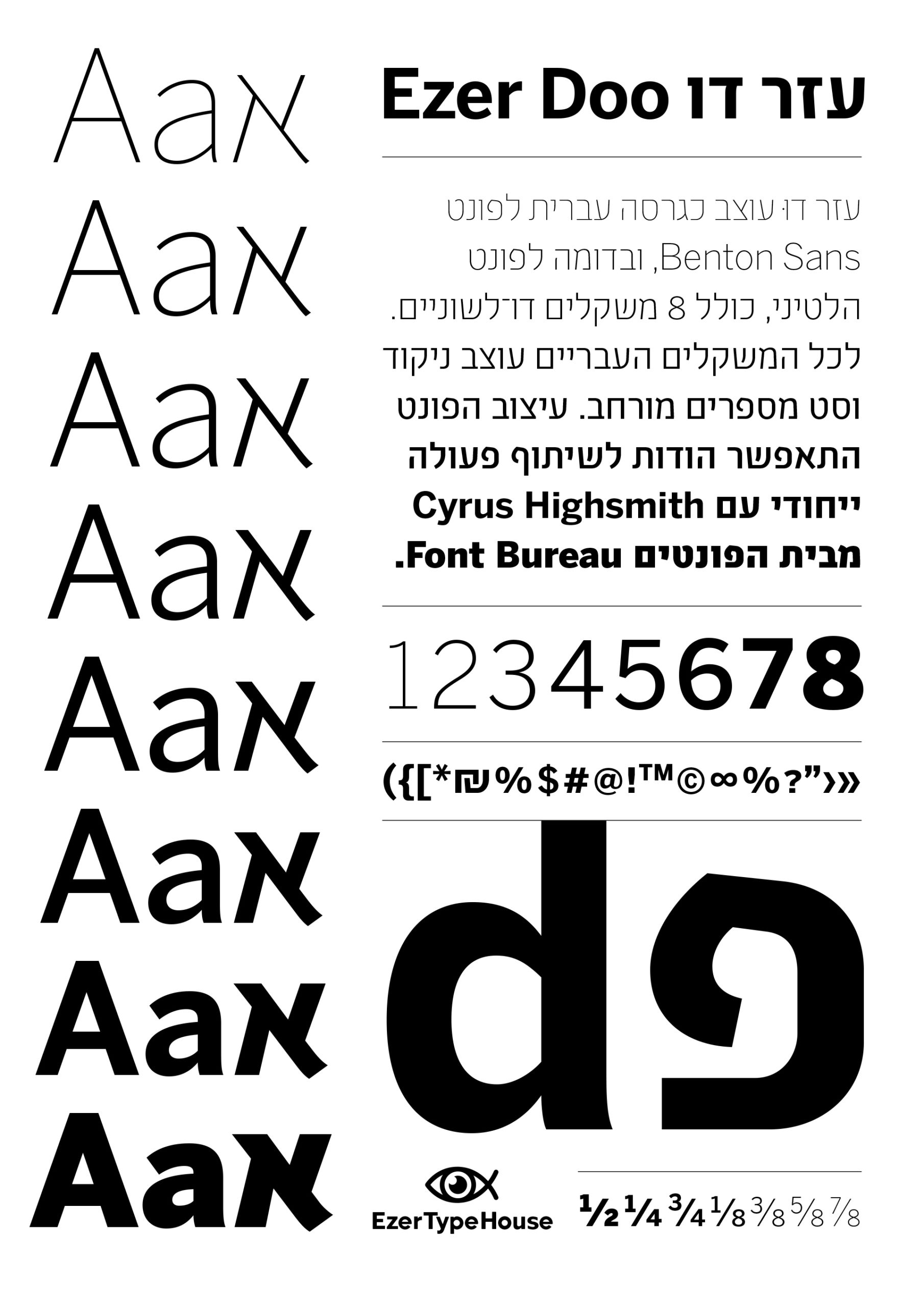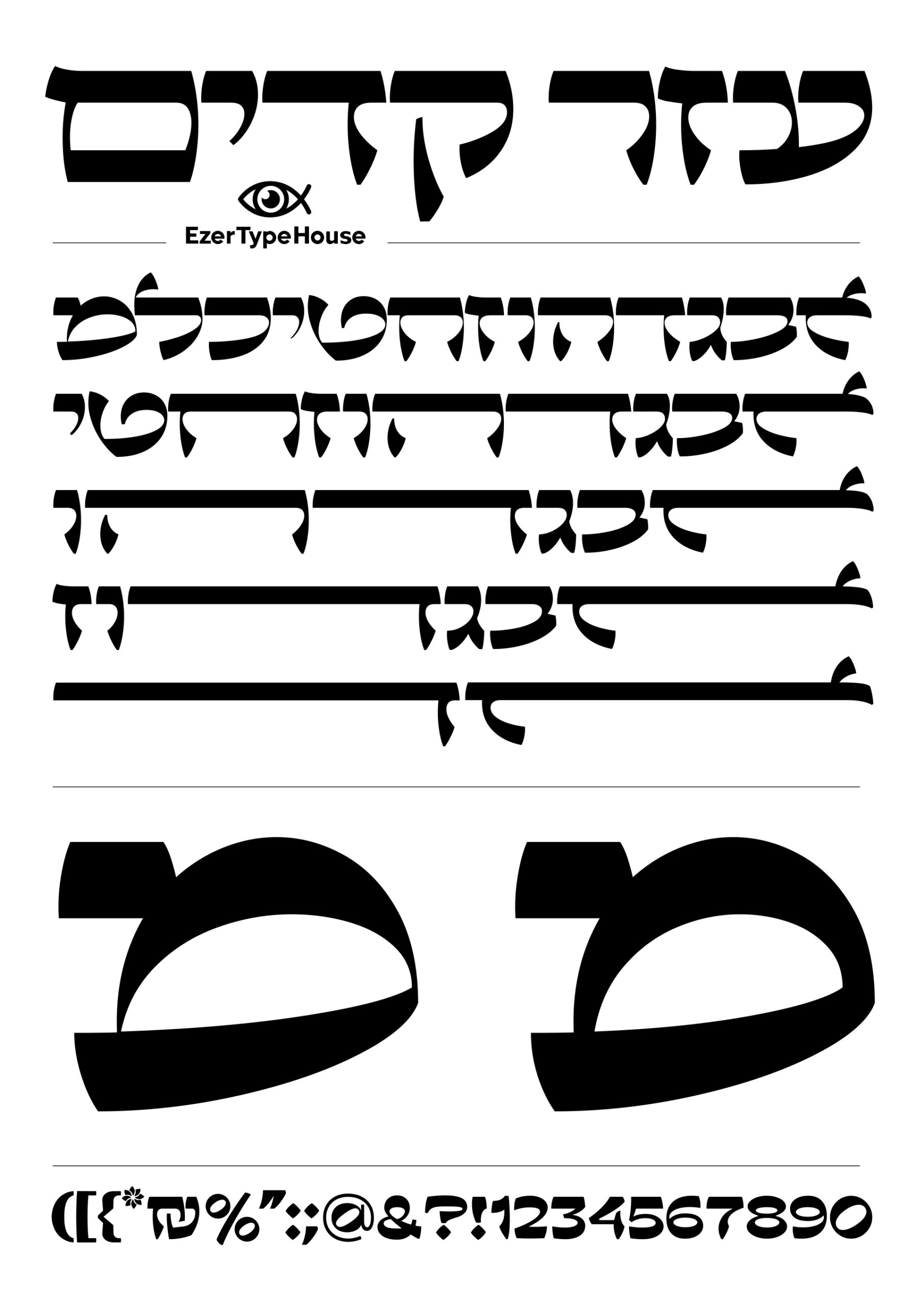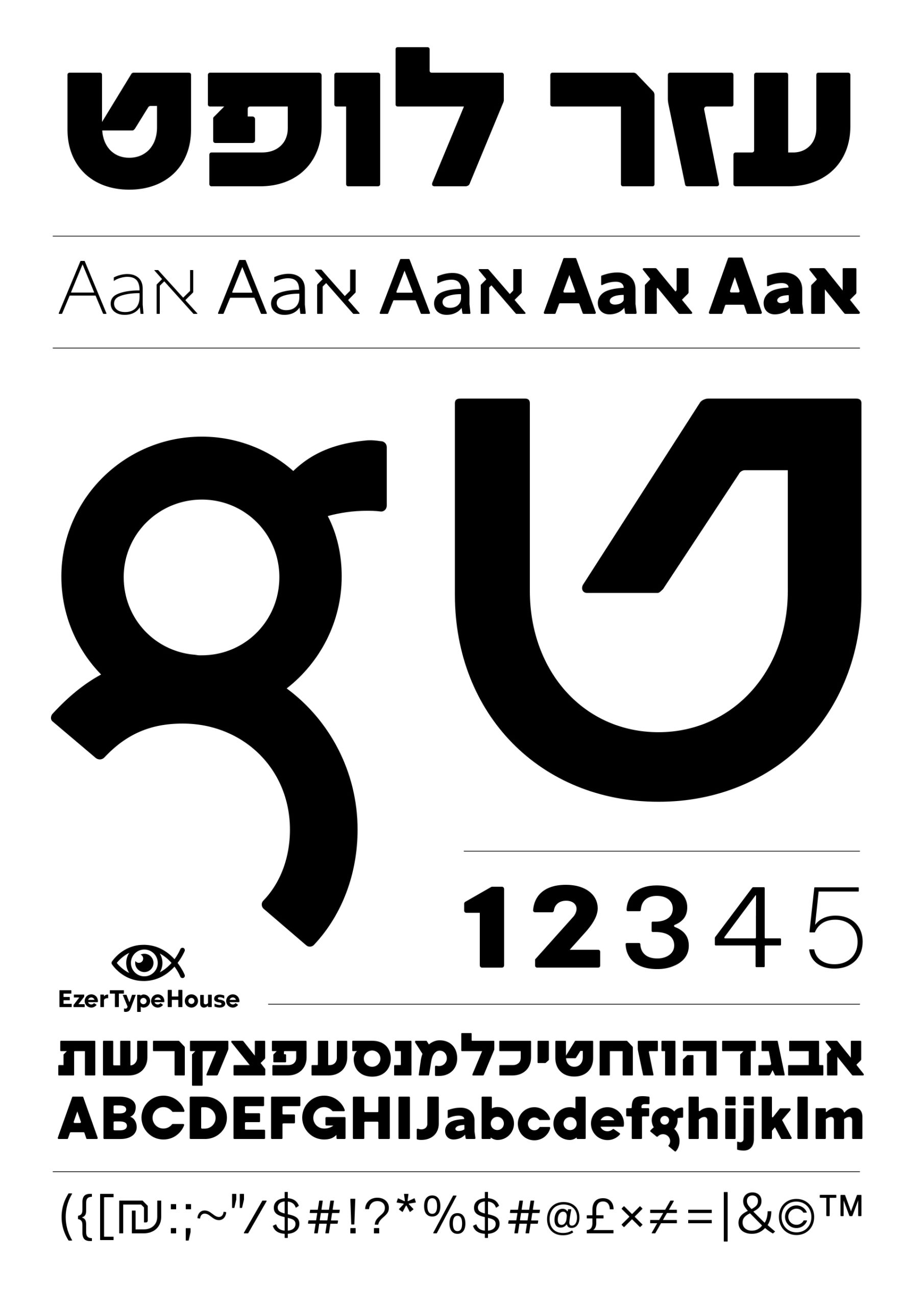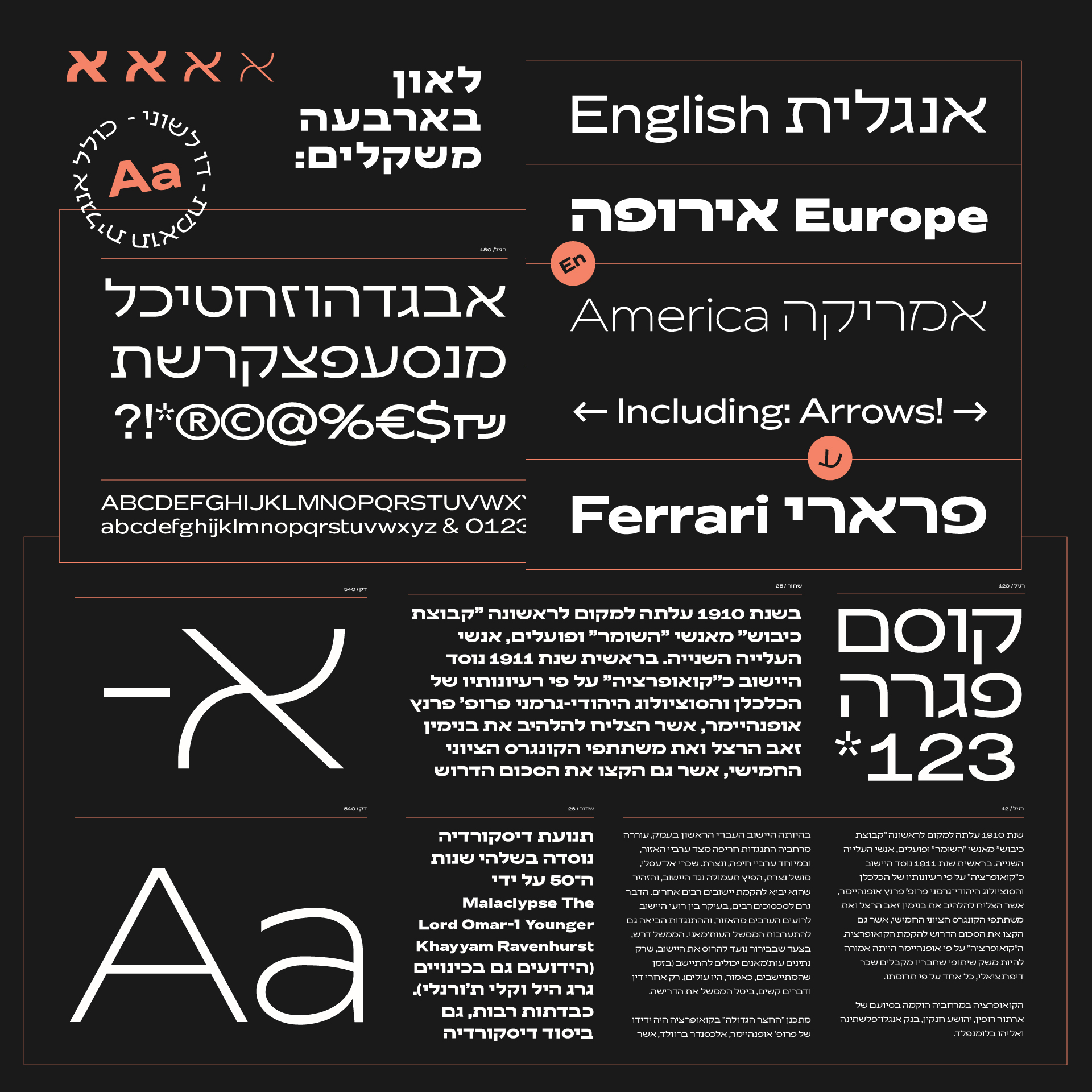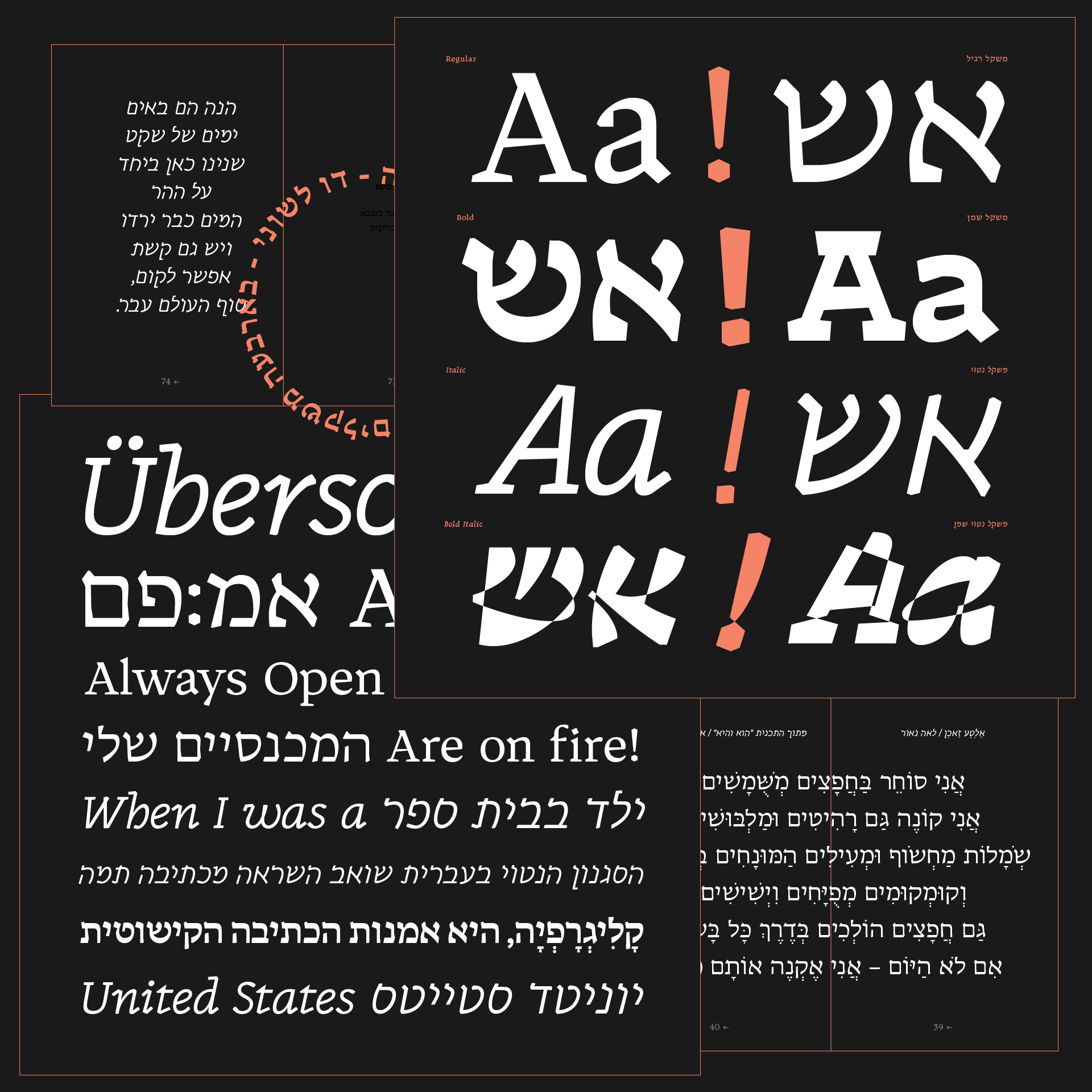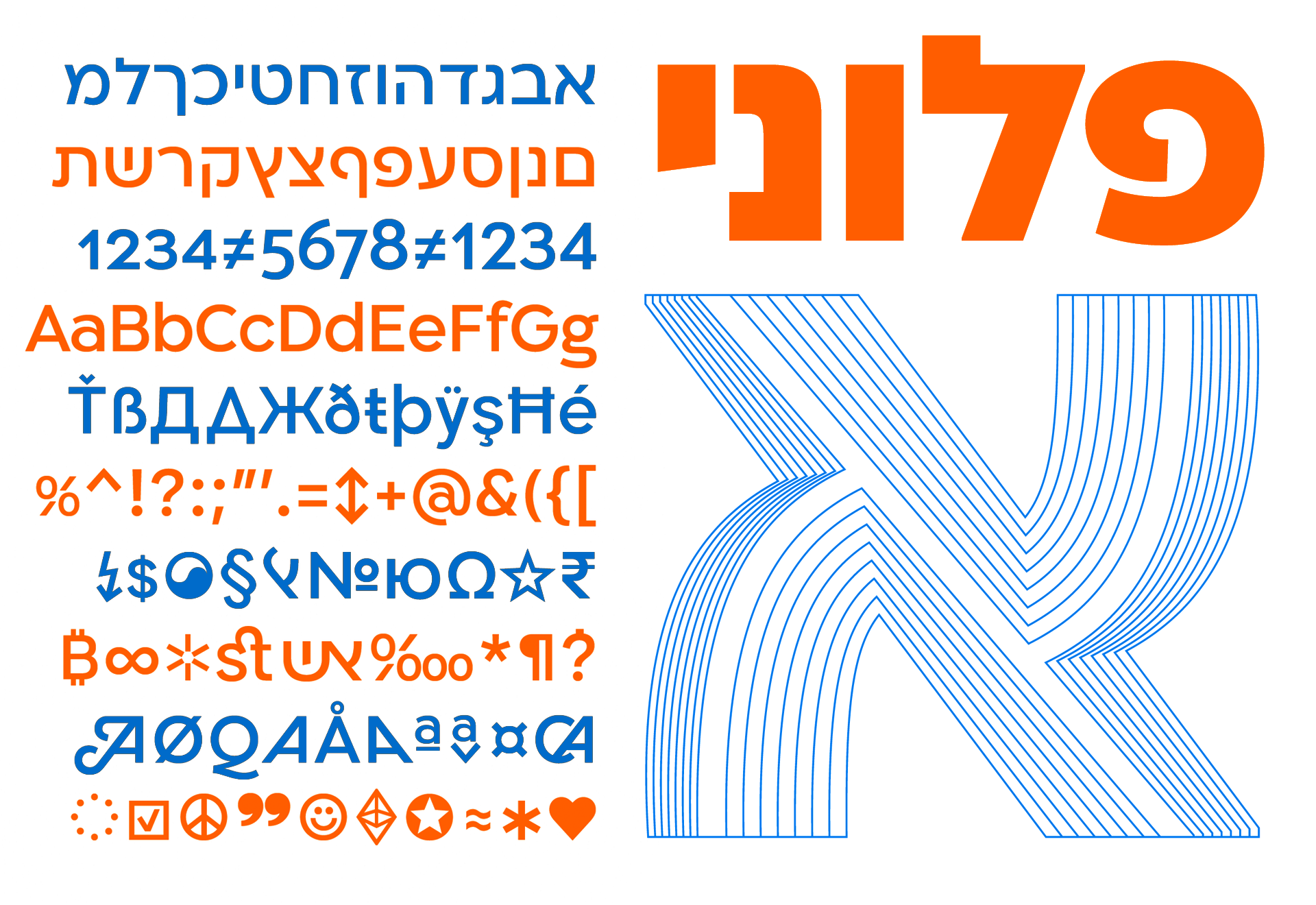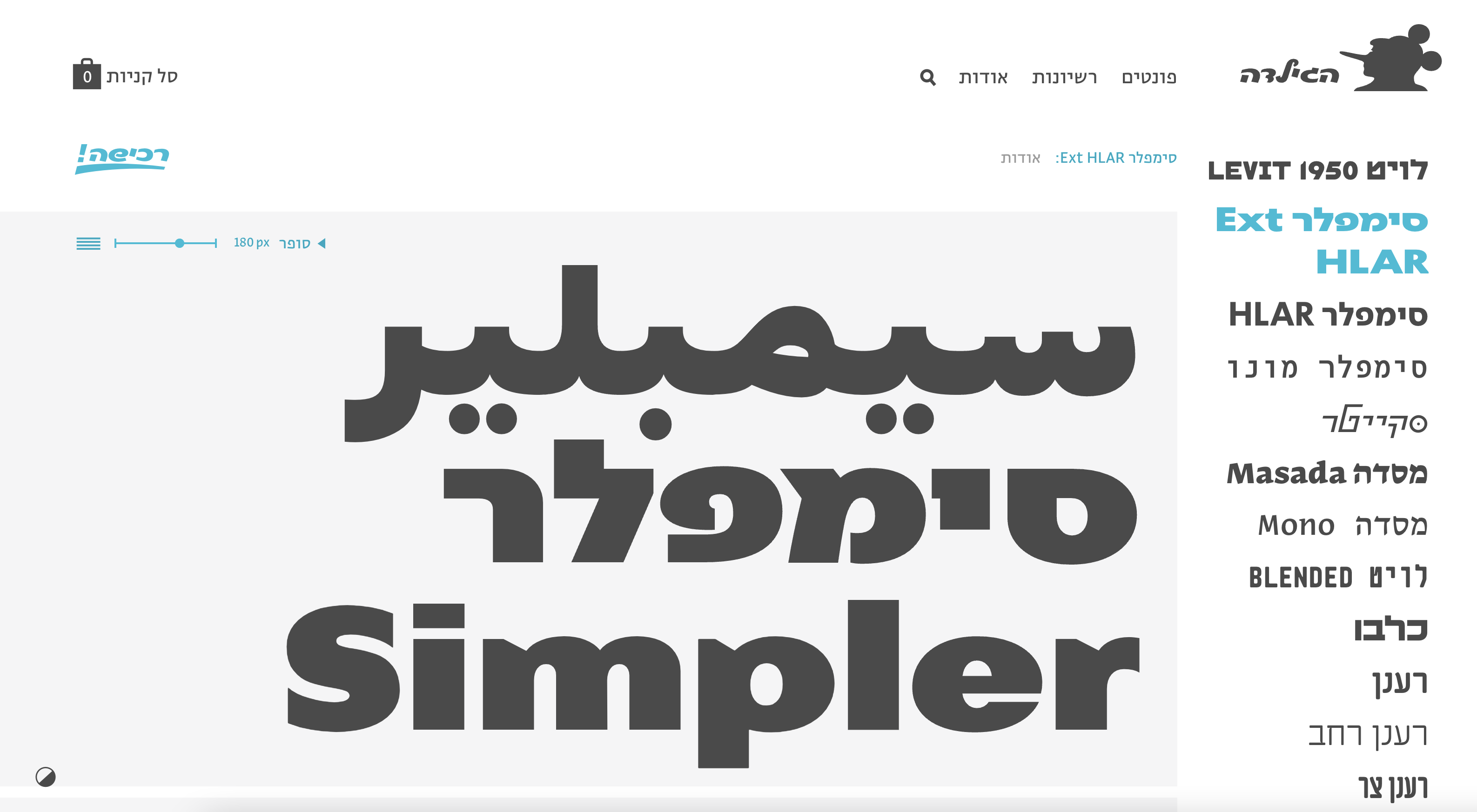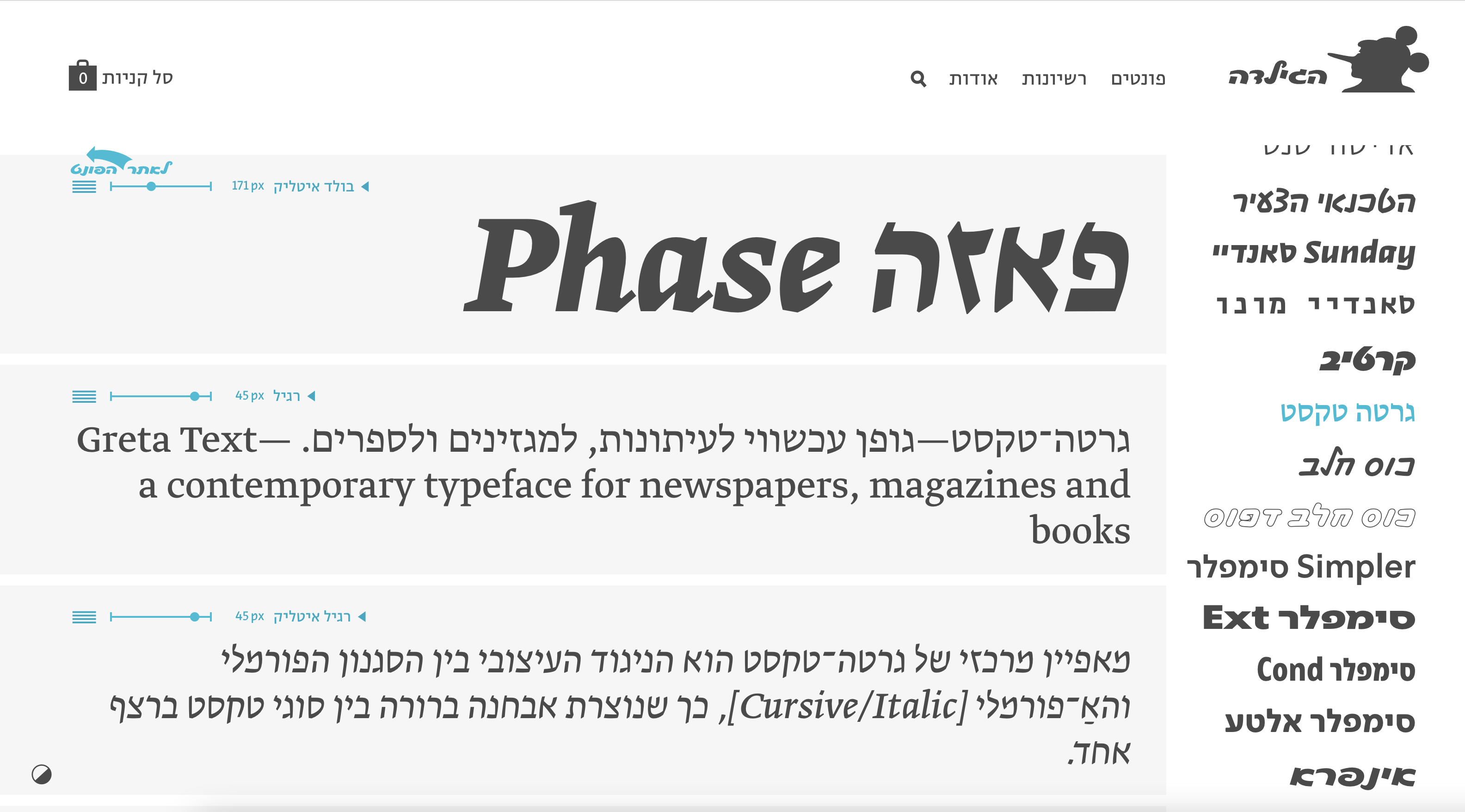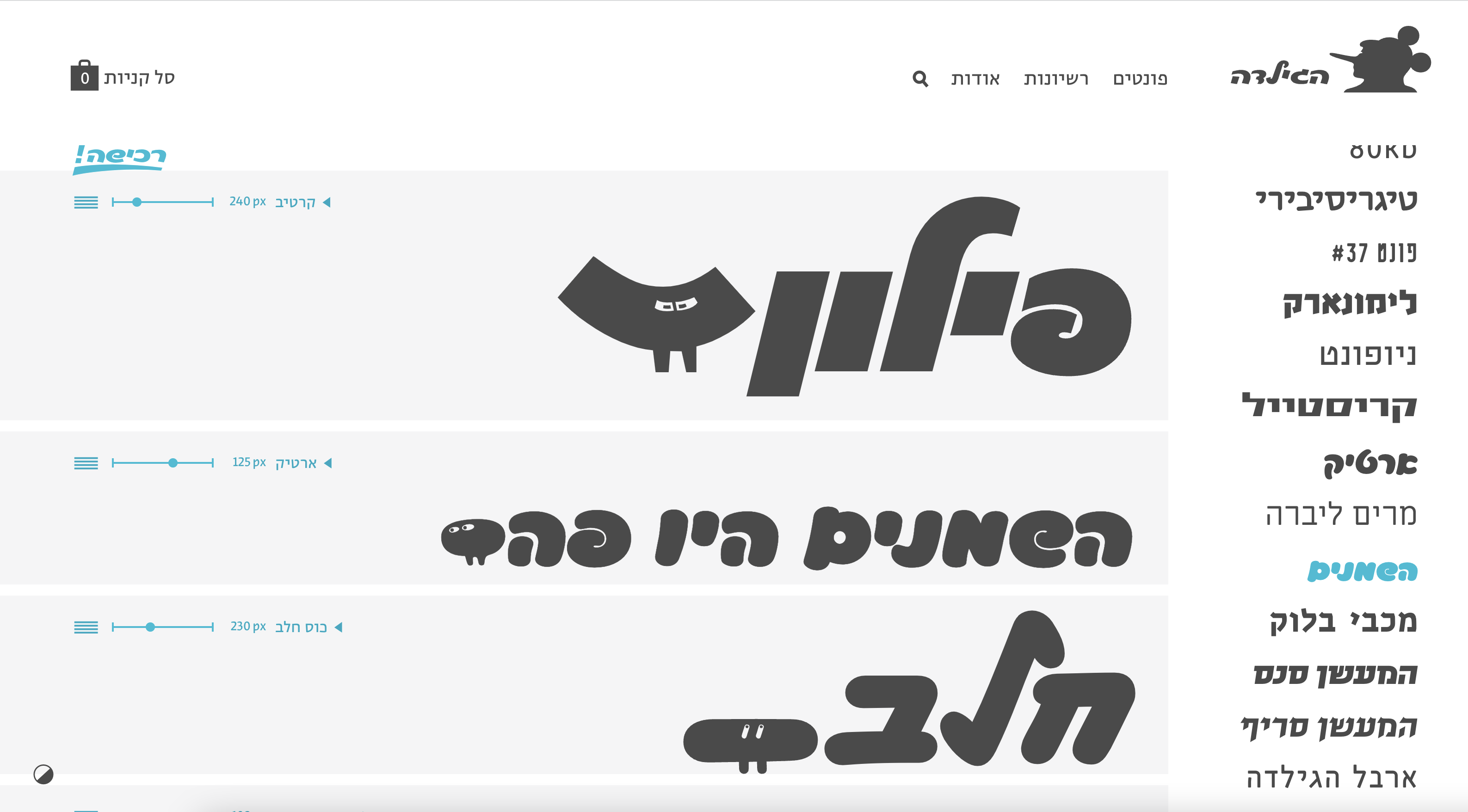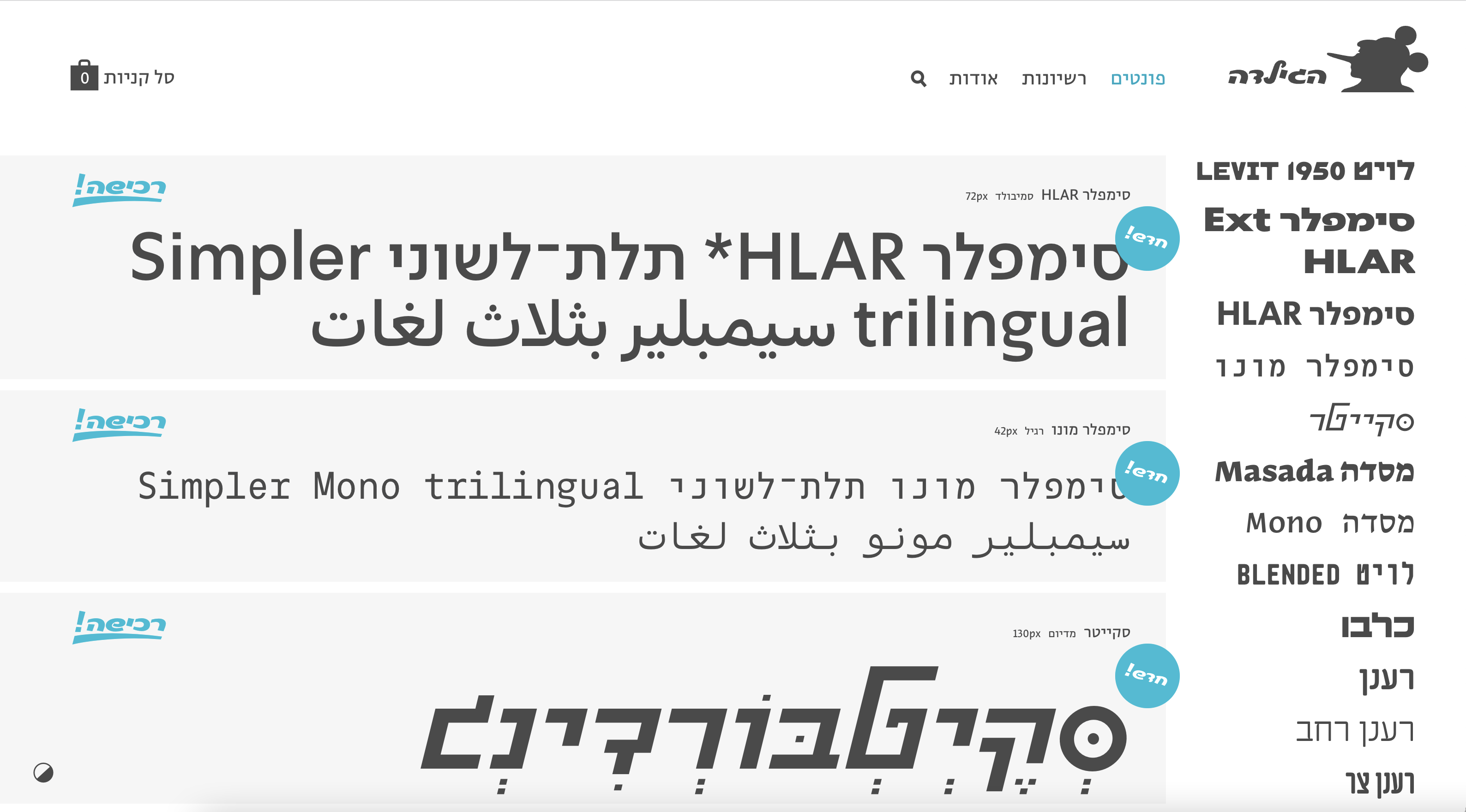
איפה הפונטים הכי יפים בעברית?
יש המון פונטים יפים בעברית, אך מי מהם הם המיוחדים, המסקרנים, המטורפים, המוזרים?
אספנו לכם כמה סטודיואים מגניבים במיוחד כדי להכניס קצת תבלינים אקזוטיים לפרויקט הבא. כתבה מתעדכנת.
פונטף
פונטף הוא סטודיו לעיצוב ופיתוח גופנים עבריים ולועזיים שנוסד בשנת 1994 על־ידי ינק יונטף. לפני כמה שנים הצטרף אליו דניאל גרומר, ויחד הם מחוללים קסמים טיפוגרפיים. בעיני, מדובר באחד הסטודיואים הכי טובים בארץ, שנע משחזור ועיבוד של פונטים ישנים, ועד עיצוב של פונטים חדשים. כל הפונטים שלהם מרהיבים ביופיים, כמו מסעדה שהולכת ומשתכללת בטעמיה, במקביל לשמירה על מסורת רבת שנים. במקביל, הם מעצבים פונטים מותאמים לגופים מסחריים: יס, IBM, גוגל ועוד.
הפונטיה
כל מי שהתחילה את דרכה בעיצוב אי-שם בשנות האלפיים כתחביב, השתמשה בפונטים של בן נתן (״הפונטיה של בן״), שהיו ידועים בתור BN. לימים, בפרויקט הגמר שלו הוא צחק על הפונטים שעיצב כנער, והיום הוא אחד הטיפוגרפים הכי מעניינים בשפה העברית. אגזים ואומר שבעיני הוא ג׳יימס אדמונסון (OH NO TYPE) הישראלי, ואני קצת חולם שהם ישתפו פעולה.
כיום הוא מנהל סטודיו עצמאי לטיפוגרפיה ביפו, מלמד במכון הטכנולוגי, ובשנה האחרונה פתח את קטלוג הפונטיה לשיתופי פעולה ומציג גם פונטים של המוזיקאי והמעצב אלון תייר. בעבודותיו בן מנסה למצוא את האיזון בין יצירת כלי עבודה איכותיים שישרתו מעצבים לשנים רבות, לבין מתיחת גבולות השפה ודחיפת האות העברית למחוזות אקספרמנטלים. הקצוות האלו מייצרות את קטלוג הפונטיה שמציע ״סוסי עבודה״ לצד משחקים בטיפוגרפיה (חכו ל-׳קורונה׳, פונט display מרהיב שייצא בעתיד).
סטודיו RAG
ראג הוא סטודיו למיתוג, טיפוגרפיה ועיצוב פונטים שהוקם על ידי אלון קנצ'וק ורמי רשתי. אחרי טיזינג של שנתיים ברשתות החברתיות הם השיקו לפני שנה את האתר החתיך שלהם, עם מעט פונטים (יחסית), אך כל פונט – מתוק אמיתי.
הם מאמינים שטיפוגרפיה היא הנכס העיצובי והטכנולוגי החשוב ביותר של מותגים היום. כמעצבים, עולם האותיות הוא מגרש המשחקים שלהם. משתמשים באותיות על מנת לעצב זהויות, ויוצרים שפות טיפוגרפיות ייחודיות עבור מותגים שרוצים לדבר אחרת.
הגילדה
הגילדה הוקמה ב־2002 כפלטפורמה קואופרטיבית לעיצוב ושיווק פונטים איכותיים ומסוקסים. מיכל סהר ודני מירב (הטייס), בוגרי בצלאל, מעצבים עצמאיים, טיפוגרפים ומרצים באקדמיה בצלאל.
חזונם הוא ליצור ולהפיץ פונטים רב־שימושיים מצויינים לשינוי מרחב העיצוב העברי והישראלי. אנחנו מהווים אלטרנטיבה למי שאכפת לו מסטנדרטים גבוהים של טיפוגרפיה, קריאוּת ועיצוב.
לאחרונה השיקו אתר חדש ונוח ומשחררים פונטים בקצב מתגבר. תענוג לראות את האותיות שעיצבו מאריזות בסופר, עיתונים, דרך תערוכות ועד מיתוגים שלמים.
עזר טייפ האוס
עזר טייפ האוס נוסד בשנת 2001 על־ידי עודד עזר, בוגר בצלאל ופרופסור לעיצוב במכון הטכנולוגי חולון. אל עזר הצטרפו ב־2020 יקיר מרדכי, מעצב דיגיטל, ורותי עזר, מנהלת עסקית.
עד כה עיצב עודד עזר למעלה מ־40 טיפוסי אות, כאלו קיצוניים, מוזרים ומרהיבים, לצד מעונבים, מהודקים לשימושים ורסטליים ביותר. בנוסף, עיצב עזר פונטים תאגידיים עבור חברות בינלאומיות ומקומיות כגון yes ,Samsung, Waze, Google, גלובס ומגדל, ואפילו עבור ליגת הרוגבי האוסטרלית (NRL).
עזר משתף פעולה באופן שוטף עם מעצבי פונטים בולטים בעולם, ביניהם עם Neville Brody, Cyrus Highsmith, Rob Keller, Henrik Kubel ו-David Jonathan Ross (שגם הומלצו במדריך פונטים באנגלית).
אאא
אברהם קורנפלד הקים את אאא בשנת 2011 מתוך אהבה לטיפוגרפיה ורצון לאפשר לכלל המעצבים בארץ גישה אל פונטים מצוינים ועצמאיים בדגש על איכות וחדשנות בתחום.
בגירסא הראשונית של הסטודיו נכללו בסופרגרופ — נדב ברקן, נוי ניימן, שני ברבר, ליה אופיר, ערן בכרך ואברהם קורנפלד, שמוביל עד היום את האופרציה. לי הם היוו לי כסטודנט בשנקר סוג של ׳ליגת הצדק׳ מקומיים.
הפונטים של אאא ״השתלטו״ על המרחב הציבורי (פתחו עיתון, הסתכלו סביבכן בסופר) והאינטרנטי, בזכות פניה לקהל רחב בגישה אמפתית, ומהווים היום מרכיב חזותי מרכזי בעולם העיצוב הישראלי.